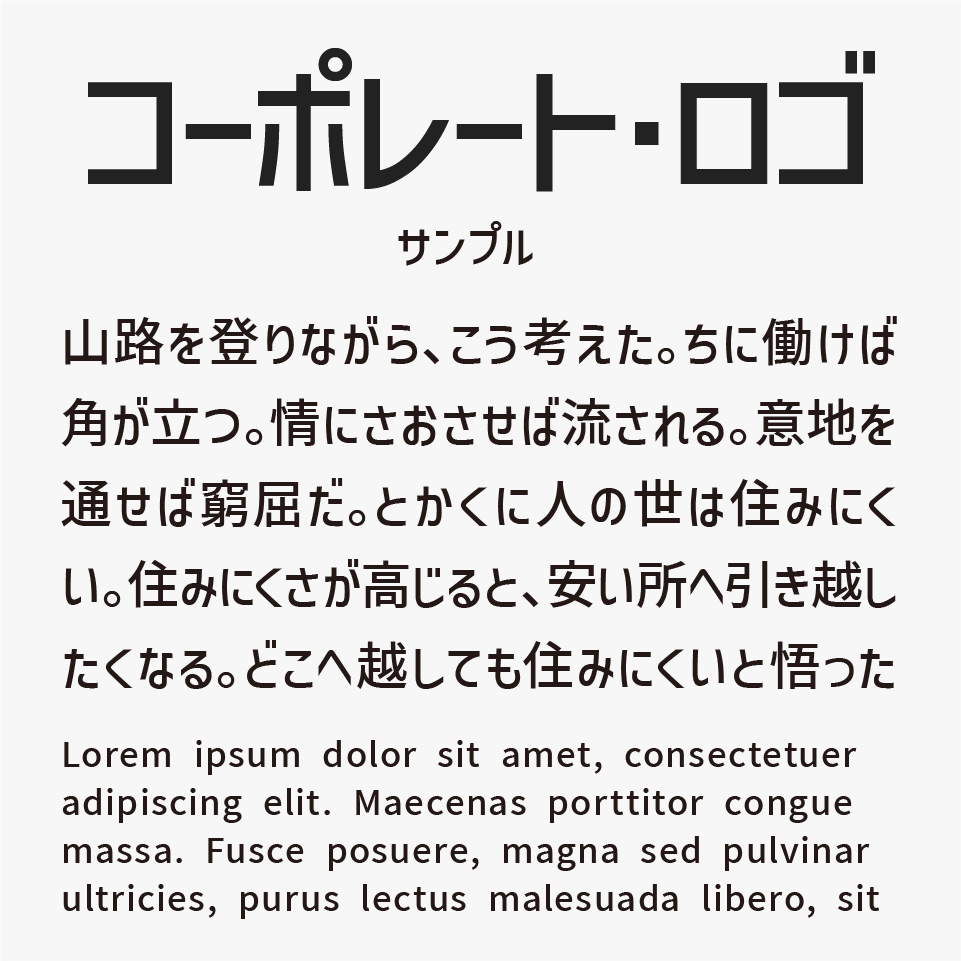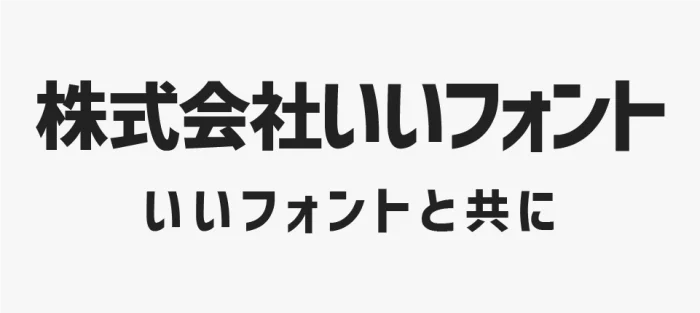
コーポレート・ロゴ
コーポレート・ロゴフォントとは、企業やサービスのロゴ・ロゴタイプとして使いやすいようにデザインされた、縦長でモダンな雰囲気のゴシック体フォントです。
企業ロゴでよく見られるような、直線的で角張ったフォルムが特徴となっており、すっきりと洗練された印象を与えてくれます。クセが強すぎないデザインのため扱いやすく、ロゴ用途はもちろん、見出しやブランディングデザインなどにも使いやすいフォントです。
簡単に文字を打ち込むだけでも、それっぽい雰囲気に仕上げやすいフォントです。(もちろん、実際のロゴ制作ではデザイナーへ依頼したり、細かな調整を加えたりすることで、より完成度の高いロゴに仕上げることができます。)
ロゴ作成時のベースフォントにも、タイトルロゴなどにも使っても良いとのことです。ウェイトもボールド体(B)とミディアム体(M)の2種類が用意されています。
角を丸くした「コーポレート・ロゴ(ラウンド)」もあるので、ぜひ比較してみてください。
収録漢字は、ひらがな・カタカナ・漢字はオープンソース「源ノ角ゴシック」で補完・記号・英数字・アルファベットが収録されています。